Знаки сравнения в рукописном шрифте: как их различать
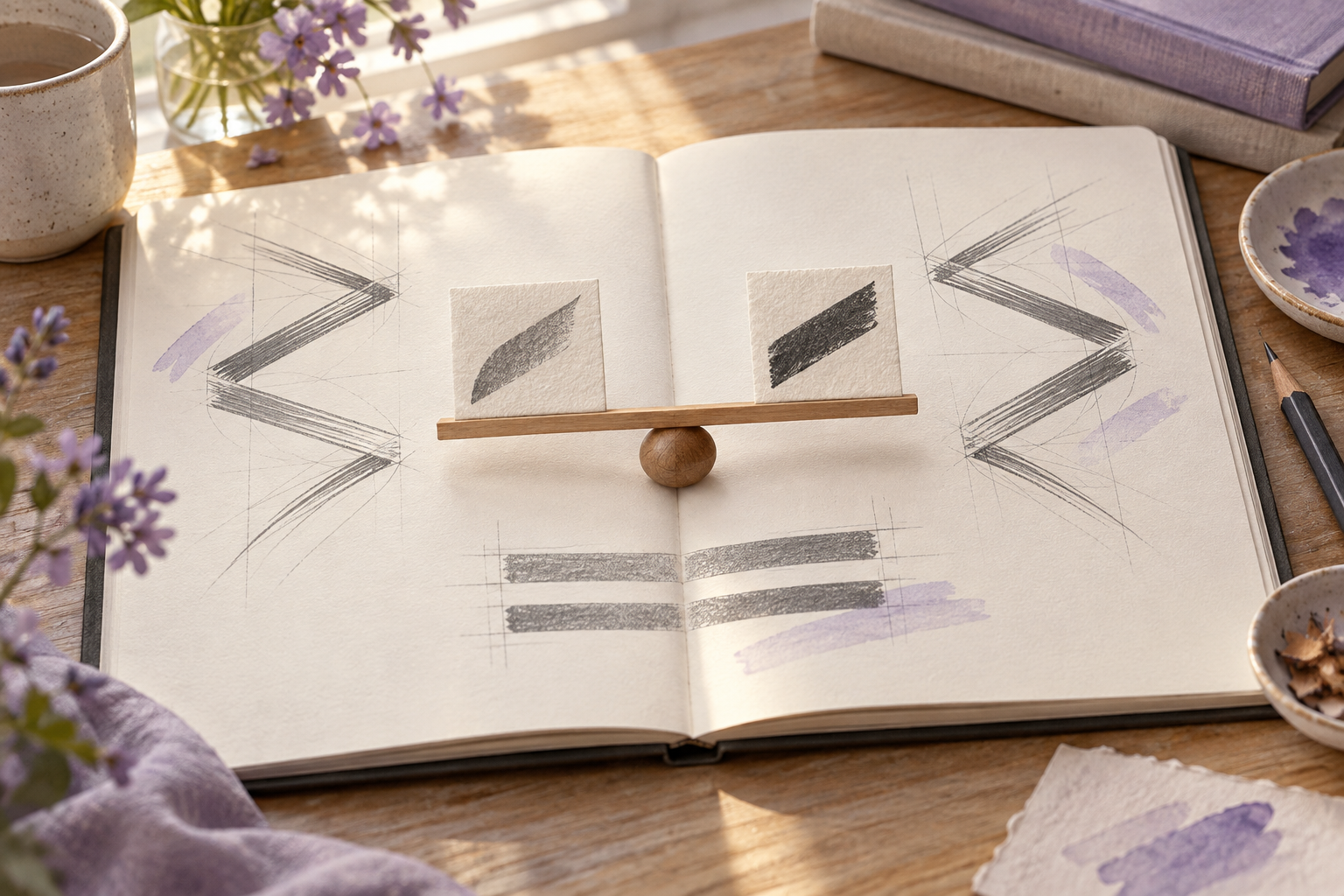
Знаки сравнения в рукописном шрифте должны мгновенно показывать направление и условие: меньше, больше, равно или «не больше / не меньше». Для этого согласуйте наклон и толщину угловых знаков, удержите равенство на одной оси и задайте постоянное положение черты у ≤ и ≥. Затем проверьте символы не по одному, а внутри коротких числовых выражений.
Сначала определите, какие знаки нужны набору
Базовая группа сравнения включает знак меньше (<), знак больше (>), равенство (=), «меньше или равно» (≤) и «больше или равно» (≥). Для учебных листов, заметок и простых диаграмм этого набора часто достаточно. Если шрифт предназначен для формул, инженерных записей или набора программного кода, список может быть шире: понадобятся, например, «не равно» (≠), приблизительное равенство (≈) и специальные варианты неравенств.
Не добавляйте редкие математические символы автоматически. Сначала соберите фрагменты, которые пользователь действительно будет набирать: задания, шкалы, подписи к графикам, выражения с диапазонами. Из этой выборки выпишите уникальные знаки и проверьте, какие из них ожидают как отдельные символы. Это помогает не спутать рисунок глифа с его техническим наличием в шрифте и не тратить время на ненужные формы.
До рисования стоит различить знак и задачу. В примере «3 < 5» угловой штрих задаёт отношение между величинами; в разметке кода такая же форма может участвовать в записи конструкции. Силуэт может быть близким, но окружение и частота употребления отличаются. Если шрифт предполагает и математический набор, и код, тестируйте обе строки: рядом с цифрами и рядом с буквами, косой чертой, скобками и точкой с запятой.
Согласуйте основу знаков < и >
Угловые знаки строятся из двух штрихов, сходящихся в вершине. В рукописной манере важно решить, будет ли вершина острой, округлённой или слегка срезанной, и сохранять это решение в обеих формах. Сначала нарисуйте один знак как базовую конструкцию, затем отразите или заново постройте его пару с тем же углом, длиной ветвей и характером окончания. Механическое отражение подходит не всегда: ручной штрих может иметь направленный контраст, поэтому оптическая пара иногда требует коррекции.
Проверьте отношение высоты знака к цифрам. Если углы чрезмерно высоки, они начинают выглядеть как крупные шевроны и перетягивают строку. Если они низкие или короткие, связь между величинами становится менее очевидной, особенно в небольшом кегле. В рукописном шрифте удобнее сначала сопоставить < и > с высотой цифр 2, 3, 5 и 7, затем оценить всю строку. Важно не совпадение с математическим шрифтом, а ясность и согласованный масштаб внутри вашей гарнитуры.
Вершина должна читаться после уменьшения. В слишком острой точке чернильный след может сливаться при печати или экранном сглаживании; в чрезмерно тупой появляется ощущение открытой скобки. Оставьте достаточно белого пространства у соединения ветвей и проверьте, не превратился ли штрих в пятно. Не придумывайте универсальный угол в градусах: его восприятие зависит от ширины знака, толщины линии, наклона письма и соседних цифр.
Сравните две ветви по зрительной массе, а не только по линейке. Пишущая рука часто давит сильнее на одном направлении, поэтому геометрически равные линии могут казаться разной толщины. Сначала сохраните естественный контраст почерка, затем при необходимости немного ослабьте тяжёлую ветвь. Для пары < и > особенно заметна несогласованность вершины: один знак может казаться резким, другой — мягким, хотя их ширина совпадает.
Сделайте знак равенства устойчивым
Знак равенства состоит из двух горизонтальных штрихов. В рукописном наборе они могут слегка подниматься или повторять наклон письма, однако расстояние между ними должно оставаться читаемым. Проверьте равенство в привычных математических строках: «4 = 4», «12 = 12» и «x = y». Если полосы слишком близки, символ выглядит как одна тяжёлая линия; если они разнесены чрезмерно, знак кажется двумя независимыми подчёркиваниями.
Учитывайте общий наклон шрифта. Угловые формы могут быть динамичными, а равенство при этом обязано визуально стоять горизонтально в собственной логике гарнитуры. Слишком заметное восходящее движение делает знак похожим на декоративную двойную черту, а провисающая форма добавляет ощущение случайной ошибки. Сравните направления линий с горизонтальными элементами знаков «Е», «Н» и цифры 4, если они есть в вашем наборе, но не копируйте их пропорции буквально.
Ширину равенства сопоставляйте с угловыми знаками и цифрами, а не с шириной всего выражения. В записи «8 = 10» оператор должен образовывать ясную паузу, но не разрывать строку. Проверьте боковые поля: если пара цифр визуально прилипает к двойной черте, увеличьте боковой просвет; если между знаком и числами возникает пустота, сократите его. Делайте поправку на форму рядом: узкая единица и широкая восьмёрка по-разному влияют на видимый интервал.
Постройте ≤ и ≥ как единую пару
Знаки «меньше или равно» (≤) и «больше или равно» (≥) совмещают угловую основу с нижней чертой. В Unicode это отдельные символы U+2264 и U+2265, а не просто два знака, поставленные рядом; стандарт также различает их с базовыми <, > и =. Это важно для набора: в цифровом шрифте наличие похожей комбинации не гарантирует, что нужный кодовый знак отображается правильным глифом. Список имён символов можно сверить в таблице математических операторов Unicode.
Решите, как нижняя черта взаимодействует с угловой формой. Она может быть отдельной параллельной линией под вершиной или более тесно связанной частью знака; выбор должен повторяться в обоих направлениях. Черта не должна касаться вершины, иначе силуэт превращается в плотный узел. Если она отнесена слишком далеко, знак распадается на два элемента и считывается как произвольная комбинация. Ориентируйтесь на ясную просветную щель между линиями в готовом размере.
Частая ошибка — строить ≤ из < и равенства как готовых знаков без проверки общей ширины и баланса. Такая сборка полезна как черновой способ понять устройство, но в конечном рисунке может дать смещённую черту, слишком длинный хвост или неровную массу. Постройте составной символ заново на том же визуальном принципе: повторите наклон, толщину и угол базовой формы, а затем подгоните нижнюю линию по оптическому центру. Сравните ≤ и ≥ рядом, а не в разных файлах.
Не путайте U+2264 «меньше или равно» с похожим знаком U+2266 «меньше над равным» (≦): их названия и кодовые позиции различаются. Если задача ограничена обычными неравенствами, обычно достаточно проверить именно выбранный знак и пару. При создании специализированного научного набора сверяйте список символов с реальными текстами и требованиями приложения, а не предполагайте, что визуально близкие глифы взаимозаменяемы.
Проверьте интервалы и ритм выражений
Операторы сравнения обычно требуют свободного места с обеих сторон, но это пространство не следует задавать только по формуле. В рукописной гарнитуре боковые выносы могут быть асимметричными, а формы цифр — иметь разную ширину. Просмотрите записи «1 < 8», «8 > 3», «12 ≤ 20» и «25 ≥ 25». Оцените, не сталкивается ли вершина с соседним штрихом и не превращается ли короткая единица в случайный пробел перед оператором.
Для оценки ритма напечатайте последовательности с повторением и сменой направления: «2 < 3 < 7», «9 > 6 > 1» и «4 ≤ 4 < 8». В длинной последовательности заметны скачки ширины и наклона, которые теряются в одиночном глифе. Полезно также сравнить одинаковые числа по обе стороны знака: асимметрия может появиться из-за формы цифр, хотя сам оператор нарисован аккуратно. Не исправляйте такую строку механически, пока не выясните, находится ли причина в глифе или интервале.
Сделайте три пробы: крупную, обычную и малую. Крупный размер показывает неровность соединения и форму концов; основной размер помогает оценить характер; маленький выявляет слипание тонких просветов и исчезновение нижней линии. Если шрифт предназначен для печати и экрана, проверяйте реальные каналы отдельно: снимок экрана с масштабом не заменяет физическую пробу, а оттиск не показывает экранное сглаживание.
Используйте шрифт в разных контекстах. Для учебной карточки важна пара цифр и оператор; для графика — подпись и деления шкалы; для кода — соседство с кавычками и угловыми скобками. В набранном тексте отдельно проверьте вставку и копирование всех пяти знаков: визуально похожие символы могут различаться по кодовой позиции. При экспорте откройте файл в целевых программах и убедитесь, что выбранный шрифт действительно применяется, а не заменяется системным.
Короткий порядок проверки
- Составьте список выражений и выпишите реально нужные операторы.
- Определите общий наклон, толщину, высоту и форму вершины для < и >.
- Нарисуйте = и проверьте расстояние между линиями в строке.
- Постройте ≤ и ≥ как парные знаки с одинаковой логикой нижней черты.
- Сравните боковые интервалы на узких и широких цифрах.
- Проверьте одиночные глифы, короткие выражения и длинные цепочки.
- Протестируйте малый размер, печать, экран и экспорт в нужные приложения.
Ошибки, из-за которых сравнение читается хуже
- Зеркально отражать знак без оптической проверки: направленный контраст почерка может сделать пару несбалансированной.
- Ставить нижнюю черту слишком близко к вершине: просвет забивается и знак превращается в плотное пятно.
- Рисовать равенство как две любые параллельные линии без проверки расстояния в малом размере.
- Подгонять все пары цифр одним интервалом: единица и восьмёрка имеют разный видимый вес.
- Считать наличие базовых < и > гарантией наличия символов ≤ и ≥ в экспортированном шрифте.
- Проверять только крупное изображение: небольшие размеры могут скрыть просветы и изменить характер соединений.
Нужно ли делать знаки < и > зеркально симметричными?
Не обязательно. Симметричная конструкция полезна как исходная схема, но направленный нажим пера и характер соединений могут потребовать оптической коррекции. Главное — чтобы пара имела общий угол, массу и размер, а направления считывались без сомнений.
Чем ≤ отличается от записи < с чертой равенства?
В наборе знак «меньше или равно» представлен самостоятельным символом U+2264, а аналогичная правая форма — U+2265. Это отдельные знаки, поэтому в шрифте проверьте наличие и отображение каждой кодовой позиции, а не полагайтесь на визуальную сборку из соседних символов.
Можно ли делать знак равенства наклонным?
Можно, если наклон согласован с общим рисунком шрифта и полосы остаются ясно различимыми. Слишком заметный подъём или провисание меняет характер знака и делает его похожим на декоративную черту. Оцените его в коротких выражениях и на небольшом кегле.
Нужно ли включать ≠ и ≈ в базовый набор?
Это зависит от текстов, для которых проектируется гарнитура. Для упражнений и простых вычислений часто хватает базовых операторов; для учебников, графиков и научных записей выборка может потребовать дополнительных знаков. Проверьте реальные образцы текста и целевые программы до завершения набора.
Как проверить, что знак не заменяется другим шрифтом?
Наберите каждый символ отдельно и внутри выражения, затем экспортируйте шрифт в целевой формат и откройте его в программе, где будет использоваться макет. Убедитесь, что выбранная гарнитура активна, а все символы сохраняют ожидаемую форму после сохранения, повторного открытия и копирования текста.
Почему ≤ и ≥ выглядят тяжелее базовых угловых знаков?
Составной знак содержит дополнительную горизонтальную линию, поэтому его площадь и плотность часто выше. Сравните толщину нижней черты с ветвями, оставьте открытый просвет и проверьте ширину в строке. При необходимости корректируйте черту отдельно, сохраняя узнаваемую связь с базовым знаком.
Рабочая группа знаков сравнения строится вокруг повторяемой геометрии и проверяется в контексте. Сначала согласуйте <, > и =, затем разработайте парные ≤ и ≥, после чего проверьте интервалы, размер и отображение после экспорта. Если вы превращаете собственный почерк в шрифт, подготовьте контрольные выражения и испытайте их в Fontgenerator на привычных вам строках.